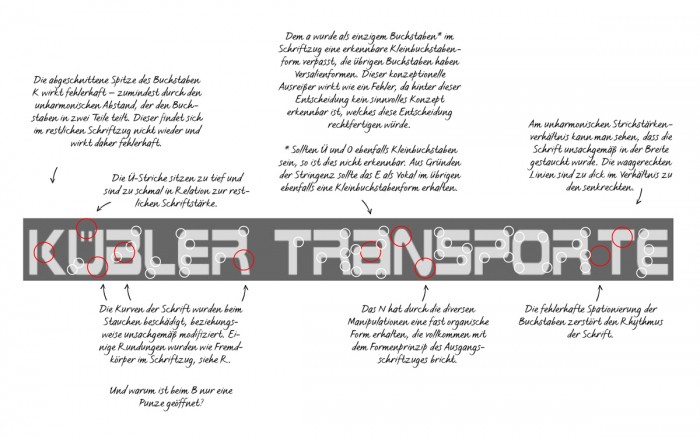
Welche Schrift ist das ?
normalerweise versuchen wir hier, Neuen nicht gleich auf die Zehen zu treten, weil wir nette, freundliche Typo-Nerds sind. Mehr oder weniger. Trotzdem von mir gleich einmal Widerspruch:
… diese Schrift brauche ich …
Nein. Niemand braucht diese Schrift. Niemand. Die sieht aus wie ein Verkehrsunfall. Man kann nicht hinsehen, man kann aber auch nicht so recht wegsehen. Glaub mir, wir bekommen hier mitunter gruslige Sachen zu sehen, aber das ist starker Tobak. Anders gesagt: Wenn »Kübler Transporte« mit Fahrzeugen unterwegs wäre, die so verbastelt sind, wie diese Schrift, kämen die nie durch den TÜV. Und falls nicht, würden die sich mit dieser Schrift völlig unverdient blamieren.
Willst Du also wirklich genau diesen Typoschrott, oder darf es eine halbwegs ordentliche Schrift mit ähnlichem Duktus sein (so weit man den erraten kann; das Muster hat ja überhaupt keinen konsistenten Duktus)?
und hier noch die antwort: die basis des schriftzugs ist ein freefont namens ›earth 2‹ (wobei hier und da händisch lücken in den buchstaben geschlossen wurden und das endergebnis ein wenig gestaucht wurde). schön ist das alles in der tat nicht. bei der ersetzung durch eine professionell gestaltete schriftart ginge ästhetisch wenig verloren.
wie pachulke schon sagte: wenn der auftritt professionell wirken soll, sollte auch eine professionell gestaltete schriftart gewählt werden. das trifft auf ›earth 2‹ nicht zu. grob ähnlich, aber wesentlich ansprechender wäre zum beispiel:
Ich habe langsam fast schon das Gefühl, dass alle, die was mit typografischer Ausbildung zu tun haben, und in Büchern wie denen von Tschichold oder Kapr nur Unfug steht.
Da geben sich die, die mit ihrer Kunst Geld verdienen wollen ab, und feilen für Monate an der Präzision ihrer Schrift, am harmonischen Zusammenspiel von Buchstaben, Ziffern und Satzzeichen.
Und dann schaue ich auf diverse Seiten, wo Leute Schriften suchen, die sie irgendwo gefunden haben, und sich dermaßen in diese Schrift verliebt haben, dass sie unbedingt genau diese klasse Schrift benötigen.
Und dann schaut man sich das vorgelegte Schriftmuster an, und was ist das? Eine zuerst einmal planlos und eiligst gezeichnete Schrift, die dann auch noch vom Anwender irgendwie verzerrt und an den Buchstaben noch herum gestutzt wurde, und Zeichenzwischenräume dann auch noch wie Ausgewürfelt wirken.
Das ist nicht nur hier oft so, sondern scheint ein richtiger Trend zu sein.
Könnte es sein, dass man, nachdem es kaum noch handgeschriebene Schilder gibt, und überall nur noch computergerierte Beschriftungen mit perfekten Satzschriften zu sehen sind, die typografisch ungeschulte Bevölkerung sich schlicht daran satt gesehen hat, und man sich nach etwas mehr ungelenker Natürlichkeit sehnt, die man dann in den verunglückten Sachen zu finden glaubt?
Ich glaube nicht, dass das ein Phänomen gerade unserer Zeit ist. Die Bücher, die du genannt hast, sind ja letztlich hauptsächlich für die da (und werden auch fast nur von denen gelesen), die sich ohnehin schon mit Typografie beschäftigt haben. Wenn man aber keine Ahnung hat (und kein Mensch kann von allem eine Ahnung haben), ist es ganz verständlich, wenn man sich in das Erstbeste verliebt, das einem begegnet. Ich zum Beispiel kenne mich überhaupt nicht mit Wein aus. Wenn ich jetzt ein Gläschen Wein trinke, und sei es der allermiserabelste Fusel, würde ich ihn auch vielleicht gar nicht so schlecht finden - aus Mangel an Vergleichen.
Liebe Brigitte, zuerst mal: fröhliche Weihnachten!  :-)
Und zu dem von Dir gezeigten Schriftzug ist tatsächlich aus typografischer und gestalterischer Sicht zu sagen, dass er leider vollkommen kaputt ist. Ich weiß nicht, wie versiert Du in diesen Dingen bist, aber wenn Du Dir den Schriftzug mal genau ansiehst, dann lassen sich folgende Mankos entdecken:
Vielleicht hilft Dir dies ja, Deinen Kunden davon zu überzeugen, dass eine Überarbeitung des Logos ratsam wäre? Denn ein derart unprofessionell gefertigtes Logo lässt die meisten Betrachter gewisse Rückschlüsse ziehen auf die Qualität der übrigen Leistungen eines Unternehmens – und das dürfte in diesem Fall ganz sicher nicht das sein, was der Unternehmer möchte …  :-)
Was natürlich letztlich nicht bedeutet, dass man so einen etwas verbastelten und verunglückten Schriftzug nicht zur Ideenvorlage für ein ordentlich gezeichnetes Logo machen kann.
Dabei muss man dann noch nicht einmal eine fertige Schrift haben, denn derartige, eher kontruierte Buchstabenformen lassen sich mit einem Vektorgrafik-Programm auch gut frei zeichnen.
Und das ist dann auch die 2. Sorte oft gesuchter Schriftarten: Sauberst gezeichnete Logos, die nur aus wenigen, unterschiedlichen Buchstaben bestehen, die sich in einer Gestaltsprache leicht und schlüssig zeichnen lassen, zu denen es aber gar keine Schriftart geben kann, weil sich manche anderen Schriftzeichen einfach nicht in die Form der wenigen Buchstaben des Logos pressen lassen, ohne dabei unschöne Kompromisse machen zu müssen.